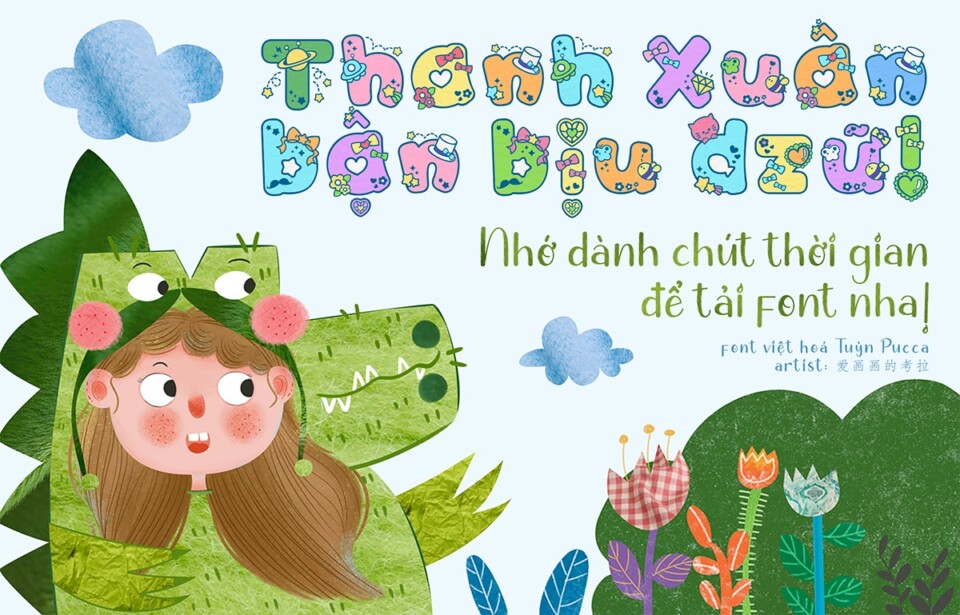
Tải Ngay Font Việt hóa TP Omekashi Font Pro – Font Chữ Thiết Kế Đẹp Mắt
Giới thiệu về Font Việt hóa TP Omekashi Font Pro
Trong thế giới đồ họa hiện đại, việc tìm kiếm một Font Miễn Phí chất lượng luôn là ưu tiên hàng đầu của các bạn học sinh và giáo viên. Font Việt hóa TP Omekashi Font Pro nổi lên như một lựa chọn hoàn hảo nhờ phong cách thanh lịch và tinh tế. Đây là bộ phông chữ được tối ưu hóa hoàn toàn cho bảng mã Telex giúp người dùng dễ dàng soạn thảo văn bản tiếng Việt mà không lo lỗi hiển thị. Với đường nét mềm mại nhưng không kém phần hiện đại, bộ font này rất phù hợp để làm báo tường, thiết kế slide bài giảng hoặc các ấn phẩm truyền thông học đường sinh động.
Đặc điểm nổi bật của Font Việt hóa TP Omekashi Font Pro
Thiết kế hiện đại và đa dạng ứng dụng
Font Việt hóa TP Omekashi Font Pro sở hữu cấu trúc ký tự độc đáo, kết hợp giữa nét truyền thống và hơi thở đương đại. Bộ font bao gồm nhiều định dạng từ mỏng đến đậm, giúp người dùng linh hoạt trong việc nhấn mạnh tiêu đề hoặc trình bày nội dung chi tiết. Đặc biệt, các ký tự đặc biệt và dấu câu trong tiếng Việt đã được căn chỉnh tỉ mỉ, đảm bảo tính thẩm mỹ cao nhất trên mọi thiết bị hiển thị.
Lợi ích khi sử dụng font chữ trong học tập
Việc sử dụng Font Việt hóa TP Omekashi Font Pro không chỉ giúp sản phẩm của bạn trông chuyên nghiệp hơn mà còn kích thích sự sáng tạo. Đối với các bạn học sinh, bộ font này giúp bài trình chiếu thêm phần lôi cuốn, tạo ấn tượng tốt với thầy cô. Trong khi đó, giáo viên có thể dùng nó để tạo ra những tài liệu học tập trực quan và dễ đọc hơn.